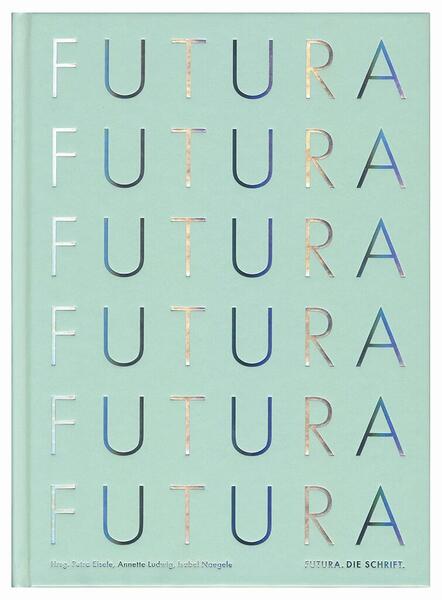
Sie markiert den Aufbruch in eine neue Gestaltung in den wilden Zwanzigerjahren des 20. Jahrhunderts. Von Frankfurt aus eroberte sie die Welt, beeinflusste das Bauhaus und wurde zu einer der beliebtesten Schriften ever. Sie beflügelte die aufkommende Werbegrafik in Europa und den USA und wurde die Schrift des Wirtschaftswunders der Sechzigerjahre. Sie war als erste Schrift auf dem Mond. Banknoten trugen ihre Ziffern und Zeichen und sie kündigte James Bond im Diamantenfieber an. Erst stand sie für Radikalität in der Gestaltung, dann für (wirtschaftliche) Solidität. Sie ist belastbar und zeitlos, war nie vergessen und ist es doch wert, wiederentdeckt zu werden.
Die Herausgeber Petra Eisele, Annette Ludwig und Isabel Naegele legen mit »Futura. Die Schrift.« ein umfassendes Werk über Entstehung, Einsatz und Wirkung der Futura vor. Die Inhalte wurden ursprünglich für die gleichnamige Ausstellung im Gutenberg-Museum Mainz zusammengetragen, für die die Direktorin Annette Ludwig als Mitherausgeberin auftritt. Für den Partner in der Hochschule Mainz arbeiteten Petra Eisele und Isabel Naegele federführend an diesem Ausstellungs- und Buchprojekt.
Das Werk besticht schon allein durch das Bildmaterial. Es wurden keine Mühen gescheut, um aus Bibliotheken, Nachlässen und privaten Archiven die bislang umfassendste bildliche Darstellung von Futura-Materialien zusammenzutragen. Und so kommt das Buch auf stolze 520 Seiten.
Ebenso beeindruckend ist die inhaltliche Auseinandersetzung. Entstehung, Einsatz und Wirkung der Futura werden umfassend und tiefgründig kulturhistorisch beleuchtet. Ausgehend vom Auftrag durch die Bauersche Gießerei bilden verschiedene Städte (Frankfurt, Hannover, Berlin, München, Wien, Prag, Paris und New York) als »Reise um die Welt« die Struktur des Buches und machen dessen größten Teil aus. Es folgen Detailinformationen zu Schriften Renners, ganzseitige Schriftmuster von Futura-Schnitten und Detailinformationen zum Entwurf.
Die Artikel stammen neben den Herausgebern von Ute Brüning, Christopher Burke, Carina Danzer, Wolfgang Hartmann (Bauersche Gießerei), Steven Heller, Stephanie Kaplan, Klaus Klemp, Iva Knobloch, Andreas Koop, Erik Spiekermann, Ferdinand Ulrich und Michel Wlassikoff.